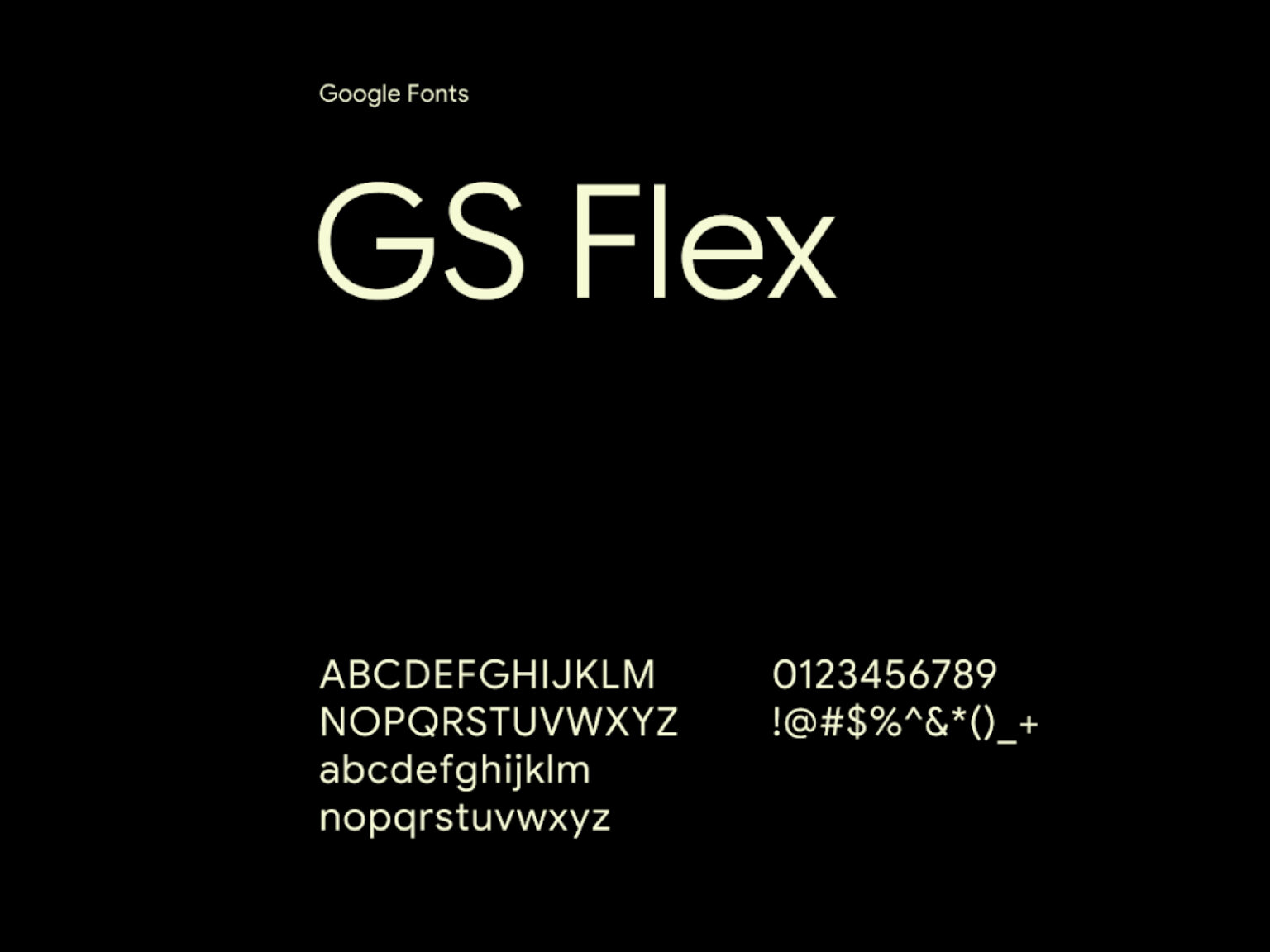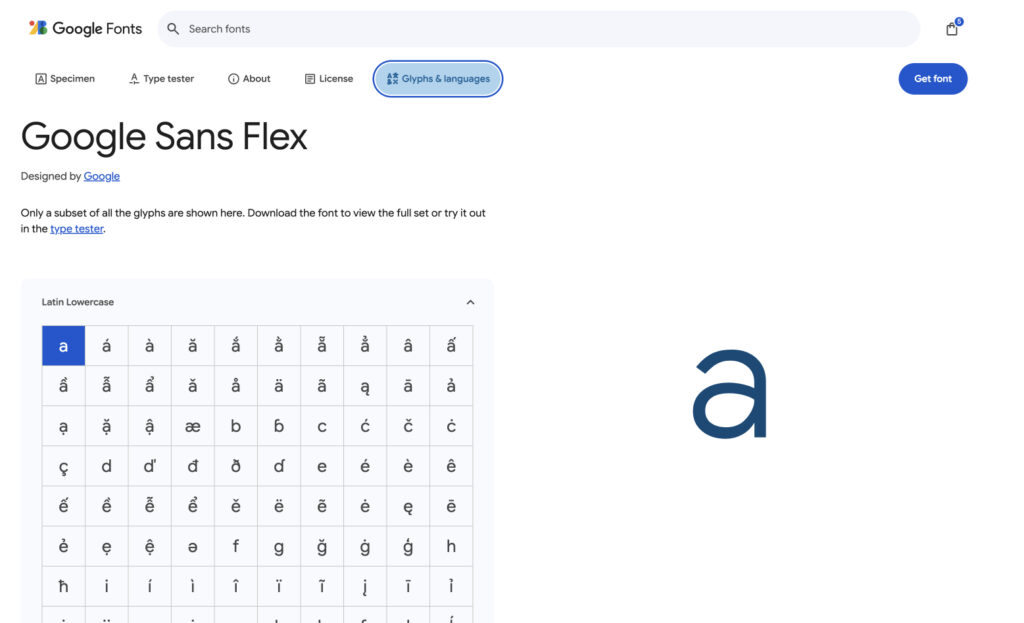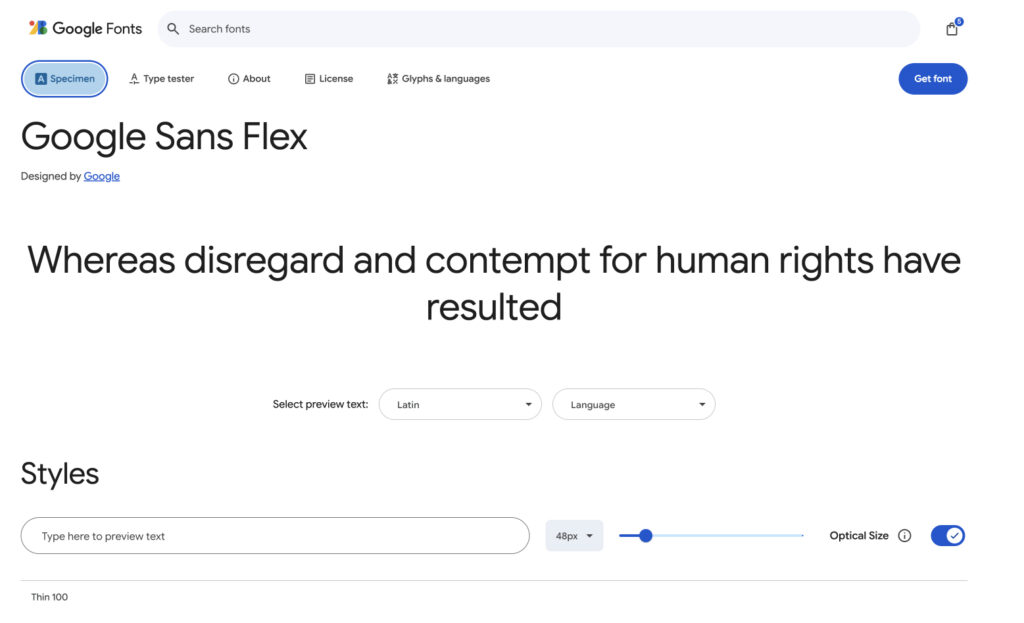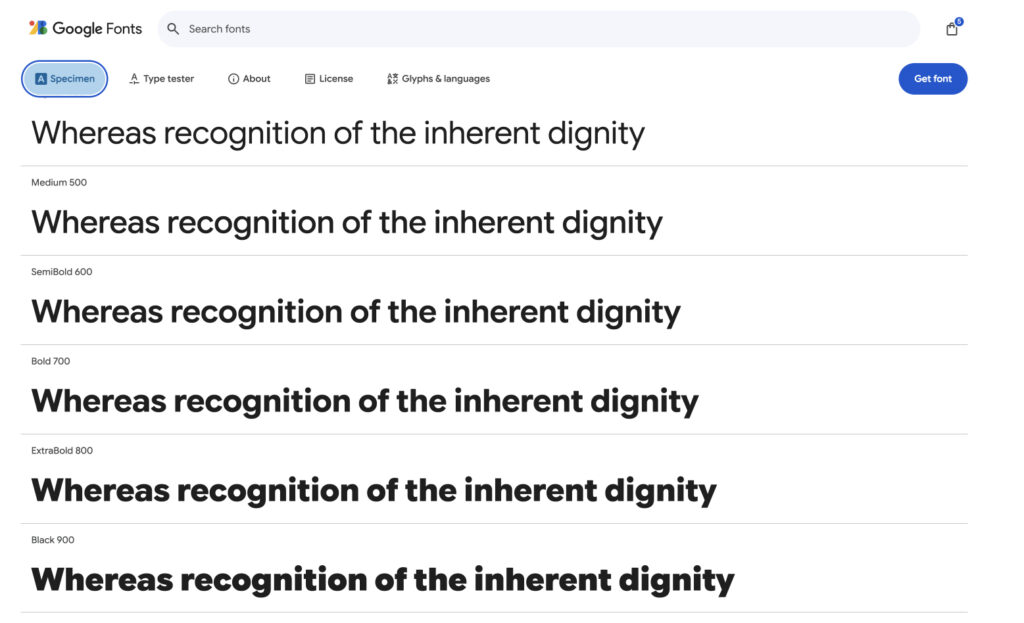
구글 산스 플렉스 폰트 무료 공개
구글이 자사 대표 서체인 구글 샌스 플렉스(Google Sans Flex)를 일반 사용자에게 완전 무료로 공개했습니다. 구글 폰트에 새롭게 추가된 이 서체는 공개 직후 전 세계 디자이너와 타이포그래피 애호가들의 높은 관심을 받고 있습니다. 구글은 수년간 픽셀 기기와 주요 서비스 화면에서 이 서체를 활용해 왔으며 이제 누구나 내려받아 상업적 프로젝트를 포함한 다양한 용도로 사용할 수 있게 됐습니다. 라이선스는 SIL 오픈 폰트 라이선스로 배포됩니다. 서체 자체를 판매하는 행위만 금지될 뿐 사용 범위는 매우 넓습니다.
구글 샌스 플렉스는 가변 폰트 기술을 기반으로 개발된 산세리프 서체입니다. 굵기와 기울기와 너비와 둥근 정도를 세밀하게 조절할 수 있어 디자인 맥락에 맞춘 다양한 형태를 구현할 수 있습니다. 구글 디자인 팀이 2024년 공개한 글에서 설명했듯 이 서체는 화면 크기에 따라 글자 형태가 자연스럽게 변하며 읽기 경험을 최적화하도록 설계되었습니다. 사용자 인터페이스 중심의 환경에서 높은 가독성을 유지하기 위해 만든 기술적 진화라 할 수 있습니다.
구글 샌스 플렉스는 구글 웹서비스에서만 보이던 고유한 인상을 유지하면서도 디자이너가 자신만의 방식으로 변형해 전혀 다른 분위기를 만들 수 있습니다. 일부 레딧 사용자들은 너비를 압축할 때 원형이 타원형이 아닌 직사각형에 가까운 형태로 바뀌는 독특한 특징을 언급하며 DIN 계열 서체를 연상시킨다는 반응을 내놓았습니다. 이런 특성은 기존 산세리프 폰트와 차별되는 디자인 실험의 여지를 제공합니다.
구글 폰트는 이미 로보토와 오픈 샌스 등 수많은 무료 서체를 제공하고 있으며 이번 추가로 브랜드 서체 공개 흐름을 더욱 강화했습니다. 디자인 퀄리티가 높으면서도 누구나 접근 가능한 서체가 늘어나는 것은 글로벌 디지털 환경에서 창작자들의 선택권을 넓히는 의미 있는 변화입니다. 구글 샌스 플렉스는 구글 폰트에서 바로 내려받을 수 있습니다.